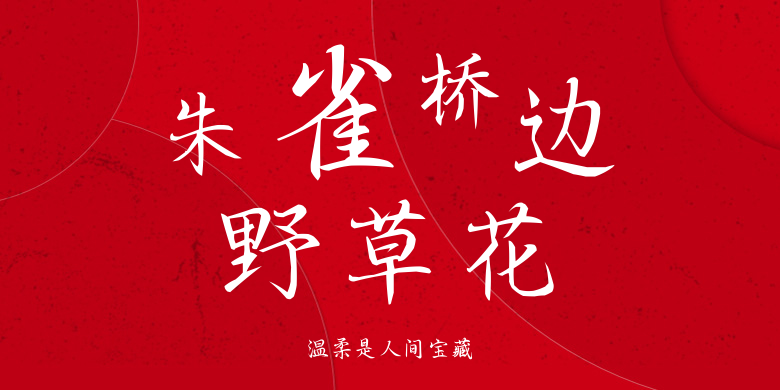
温柔是人间宝藏
温柔是人间宝藏,这款字体结构工整、笔画清晰,兼顾美观与易读性,适用于标题、正文、海报、包装、LOGO 等多种场景。字形优雅稳定,风格百搭耐看,适配日常排版与创意设计,让文字呈现更舒适、更具质感。温柔是人间宝藏一笔一画,皆是细节,以均衡的比例、流畅的线条打造舒适视觉体验,字形端正大气,风格简约现代。无论是商业设计、品牌宣传还是日常排版,都能轻松驾驭,让文字更有格调与力量。温柔是人间宝藏字体下载。